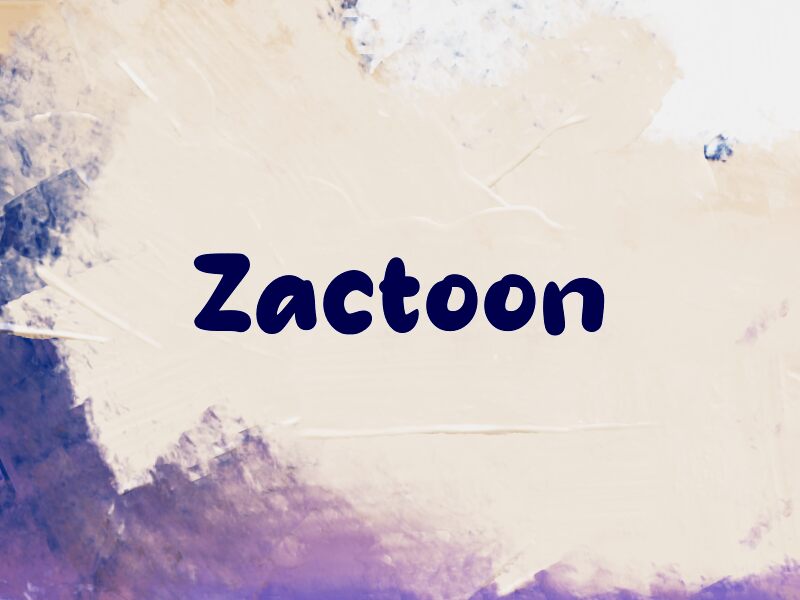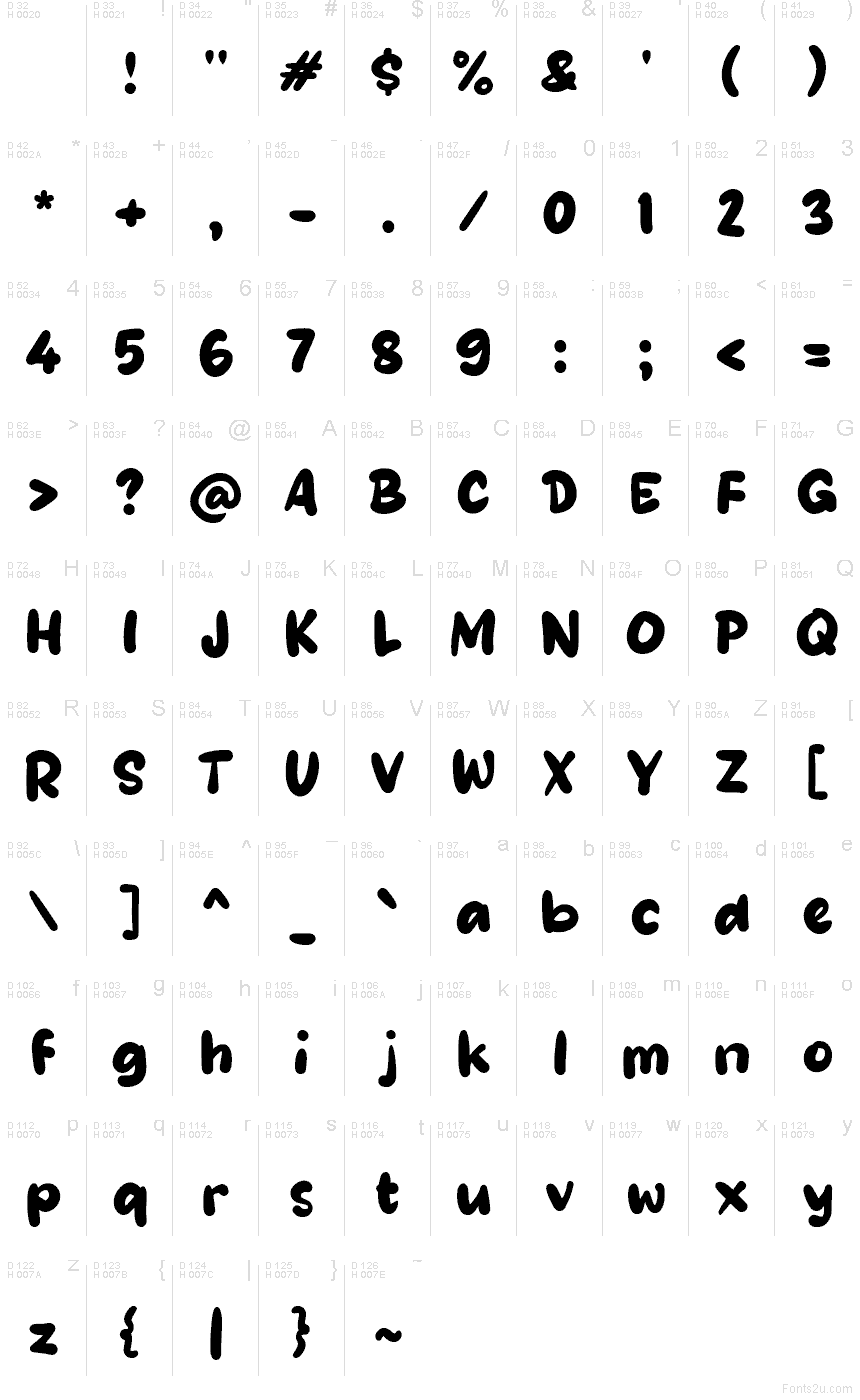
Zactoon
Zactoon от Wep - это бесплатный акцидентный шрифт в мультяшном стиле. Широкие, объемные очертания и мягкие изгибы делают каждую букву слегка «надутой». Округлые формы гармонично сочетаются друг с другом, придавая шрифту живой, рукописный характер - без излишней глянцевости, свойственной комиксам.
Такая мягкая объемность отлично смотрится в коротких заголовках на детских плакатах, упаковках снеков, наклейках, приглашениях на дни рождения и забавных миниатюрах для YouTube. Поскольку формы напоминают мягкие пятна, а не строгие печатные буквы, Zactoon отлично подходит для логотипов и заголовков, которым нужно придать дружелюбный, задорный тон, избегая при этом излишней неряшливости.